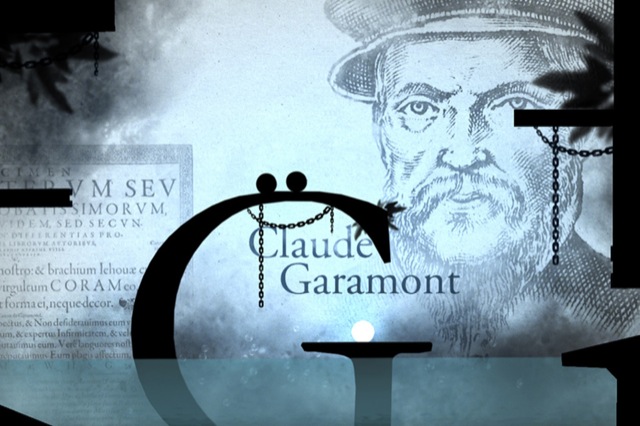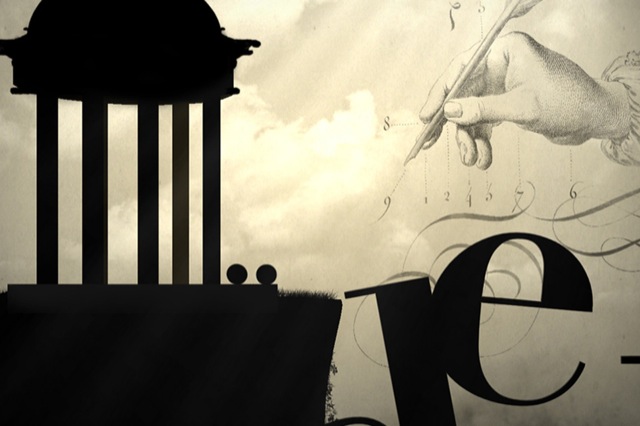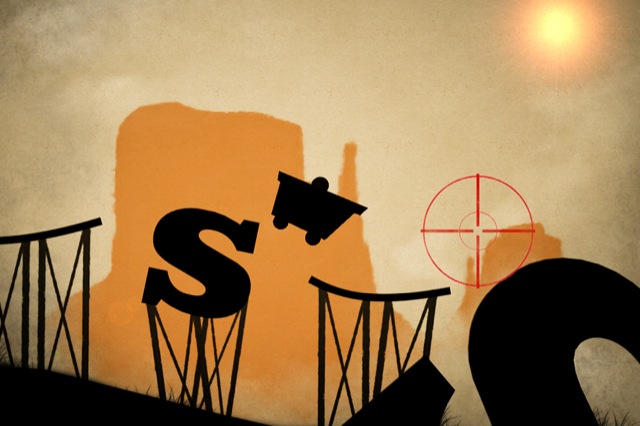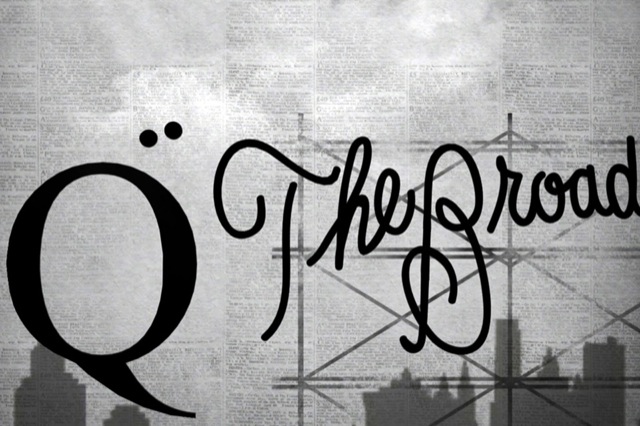
Mit Type:Rider hat der Spieleentwickler Bulkypix ein weiteres Spiel im App Store veröffentlicht.
Type:Rider (App Store-Link) ist einfach nur toll. Das Spiel lässt sich zum Endkostenpreis von 2,69 Euro laden und installieren und wartet mit tollen Grafiken und Sounds auf. Neben dem eigentlichen Gameplay verfolgt man die Geschichte der Buchstaben und schreitet durch die Geschichte der Schriftarten.
Gespielt wird mit einem Doppelpunkt, der sich über einfache Klicks über das Display steuern lässt. In einer Welt aus wunderschönen, aber auch minimalistischen Grafiken, lassen sich die zwei Freunde über diverse Objekte steuern. Passend zum Thema stößt man auf viele Schriftzeichen, muss Objekte wie Bücher oder weitere Kugeln bewegen, schwimmt durch Wasser und bekommt zudem noch einen schönen und entspannenden Soundtrack im Hintergrund abgespielt – genau aus diesem Grund wird auch die Benutzung von Kopfhörern empfohlen.
So durchläuft man die Geschichte der Höhlenmalerei der Steinzeit bis hin zur Pixel-Art im heutigen Zeitalter und trifft dabei immer wieder auf kleine Rätsel, die gelöst werden müssen. Diese sind leicht zu überwinden und stellen den Spieler vor keine unüberwindbare Hürde, sondern dienen als nette Extras im Spiel.
Jedes der 10 Level besteht aus vier Abschnitten, die sich in entsprechenden Bücher finden lassen. Ziel ist es alle verstreuten Buchstaben wieder zu finden, um so das Alphabet zu vervollständigen. Type:Rider legt das Augenmerk auf bildschöne und formvollendete Grafiken, sowie auf einen kreativen und entspannenden Soundtrack.
Viel Action sollte man nicht erwarten; in Type:Rider taucht man in einer andere Welt ab und kann sich ohne viel Ablenkung durch die Welt der Schriften spielen. Wir finden: Das Zusammenspiel aus Steuerung, Grafik und Sound ist nahezu perfekt und somit gibt es von unserer Seite auch eine klare Empfehlung. Der Download kommt dabei auf eine Größe von 225 MB und liegt komplett in deutscher Sprache vor. Unser Video (YouTube-Link) im Anschluss zeigt eines der zehn Level, wir hoffen natürlich auf weitere Inhalte per Update seitens der Entwickler.